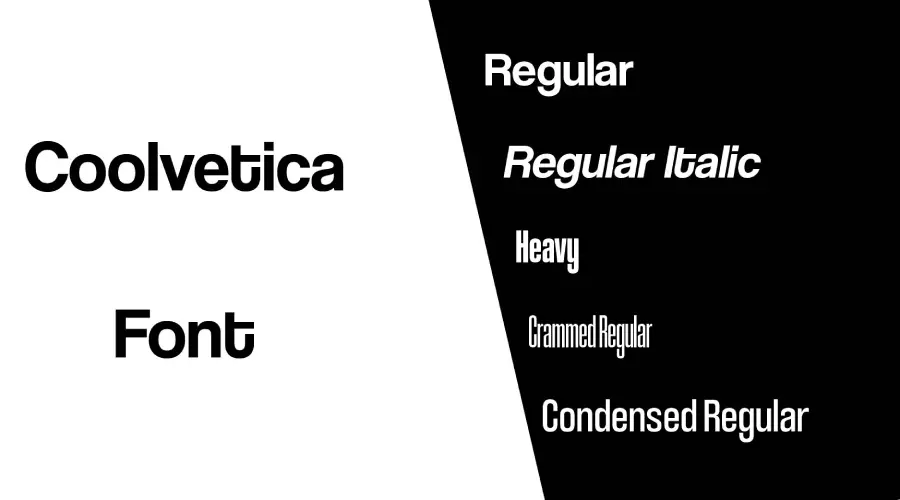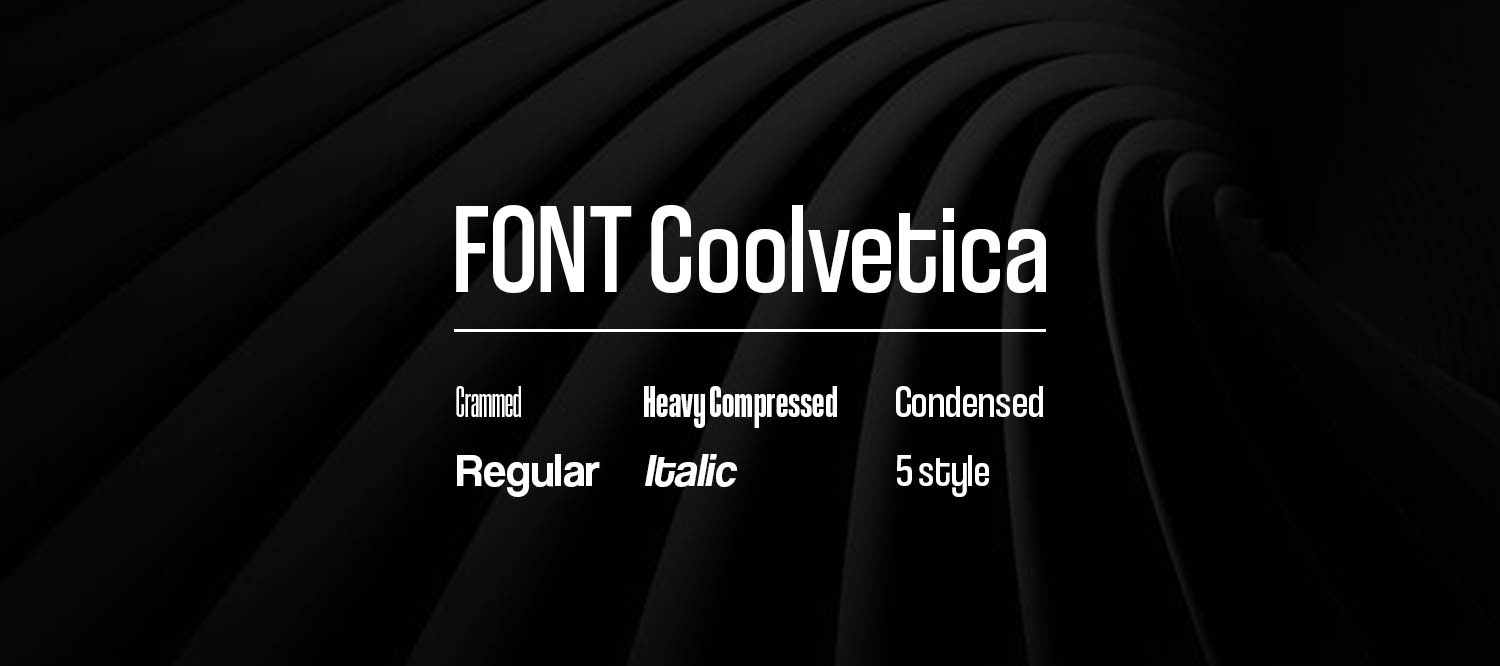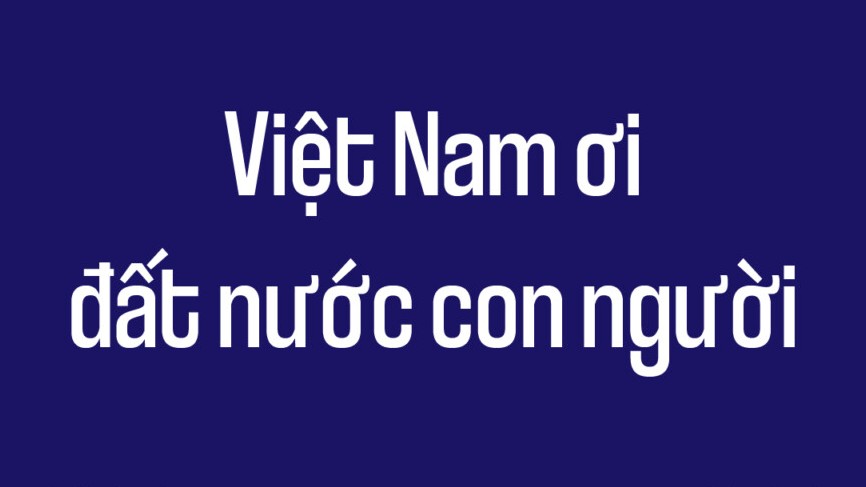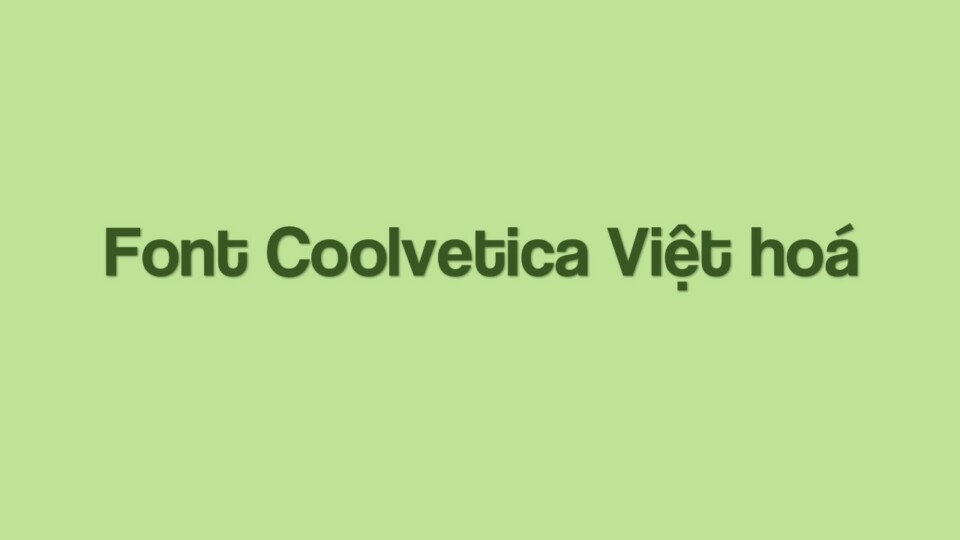
Font Coolvetica là bộ phông chữ không chân (Display Sans-serif) bán hình học nổi tiếng được sáng tạo bởi nhà thiết kế Ray Larabie (Typodermic Fonts) vào năm 1999. Lấy cảm hứng từ trào lưu biến tấu logo Helvetica đầy ngẫu hứng trong văn hóa quảng cáo Mỹ thập niên 1970, Coolvetica mang lại diện mạo vừa cổ điển, vừa tân thời với những đường cong phá cách ở đuôi chữ và khoảng cách chữ (kerning) cực kỳ ôm sát. Doozypack.vn cung cấp link tải Font Coolvetica Việt hóa chuẩn kỹ thuật, giúp bạn sở hữu phông chữ đậm chất đồ họa này mà không lo gặp bất kỳ lỗi hiển thị dấu thanh nào khi thiết kế bao bì.
Đặc điểm thẩm mỹ độc đáo của bộ font Coolvetica
Coolvetica không phải là một bản sao chép đơn thuần của Helvetica; nó là sự nổi loạn đầy phong cách, biến một phông chữ chuẩn mực trở nên sống động, trẻ trung và giàu tính biểu cảm hơn.
Cảm hứng từ phong cách Typography thương hiệu thập niên 70
Đặc trưng lớn nhất của Font Coolvetica là khoảng cách giữa các con chữ được kéo sát lại gần nhau một cách có chủ đích (tight tracking), tái hiện phong cách Typography thịnh hành trên các bảng hiệu disco, bìa đĩa nhạc vinyl và bao bì sản phẩm những năm 1970. Cấu trúc chữ sở hữu độ dày nét chắc chắn, hình khối vững chãi tạo ra một sức nặng thị giác vượt trội, giúp các dòng tiêu đề trên vỏ hộp ngay lập tức chiếm trọn ánh nhìn của khách hàng từ khoảng cách xa trên kệ hàng.
Những đường cong cách điệu phá cách trên nền tảng Helvetica
Điểm làm nên sự khác biệt của Coolvetica Regular nằm ở các nét móc uốn cong bất ngờ ở những ký tự như ‘t’, ‘y’ và ‘g’. Thay vì kết thúc bằng những đường cắt thẳng khô khan, các nét móc này mang lại cảm giác vui tươi, sành điệu và đậm chất nghệ thuật đường phố, cực kỳ ăn ý với các thương hiệu thời trang Streetwear, đồ uống giải khát hoặc các sản phẩm công nghệ hướng đến giới trẻ Gen Z.
Ưu điểm nổi bật của bản Font Coolvetica Việt hóa
Khi ứng dụng các phông chữ có khoảng cách chữ hẹp vào thị trường trong nước, sự chỉn chu về dấu câu là yếu tố quyết định đến tính chuyên nghiệp của bản thiết kế:
- Khắc phục triệt để lỗi dấu tiếng Việt: Phiên bản Font Coolvetica Regular Việt hóa đã được đội ngũ thiết kế trau chuốt thủ công từng dấu câu. Các dấu sắc, huyền, hỏi, ngã, nặng được vẽ thanh thoát, đặt ở vị trí cân đối so với thân chữ, không gây cảm giác chắp vá hay va chạm vào các ký tự đứng liền kề.
Ứng dụng thực tế của font Coolvetica trong sản xuất bao bì tại Doozypack.vn
Sự phá cách và năng động của Coolvetica mang lại hiệu ứng thị giác đắt giá trên các dòng sản phẩm bao bì thực tế do Doozypack.vn sản xuất:
- Hộp giấy thời trang Streetwear & Sneakers: Tiêu đề thương hiệu in bằng font Coolvetica trên túi giấy Ivory cán màng mờ tạo phong cách bụi bặm, nổi loạn và khẳng định cá tính riêng biệt.
- Bao bì đồ ăn nhanh & Thức uống giải khát: Nét chữ to bản gợi cảm giác ngon miệng, rất hợp làm tiêu đề chính trên hộp pizza, hộp gà rán hoặc nhãn dán lon nước ngọt phong cách Retro.
- Tem nhãn dán Sticker & Decal ván trượt: Với hình khối chắc chắn, font Coolvetica cực kỳ phù hợp để in các tem decal tròn hoặc tem niêm phong kiện hàng cho giới trẻ.
03 Lưu ý kỹ thuật khi in ấn với phông chữ khoảng cách hẹp Coolvetica
Việc sản xuất bao bì thực tế sử dụng các phông chữ có khoảng cách chữ hẹp đòi hỏi sự am hiểu kỹ thuật chuyên sâu tại xưởng in Doozypack.vn:
- Kiểm soát hiện tượng tràn mực (Dot Gain) tại các điểm giao nét: Các khoảng hở giữa những chữ cái đứng cạnh nhau khá nhỏ. Designer cần kiểm soát kỹ file in trên máy tính để đảm bảo các chữ cái không bị dính nét khi in Offset số lượng lớn.
- Lựa chọn hệ màu sắc tương phản mạnh: Phong cách Coolvetica đẹp nhất khi phối với các tông màu tươi sáng hoặc màu tương phản mạnh (chữ vàng viền đen, chữ trắng trên nền đỏ). Một đường viền (Stroke) mỏng quanh chữ cũng giúp tiêu đề trông nổi bật hơn trên vỏ hộp.